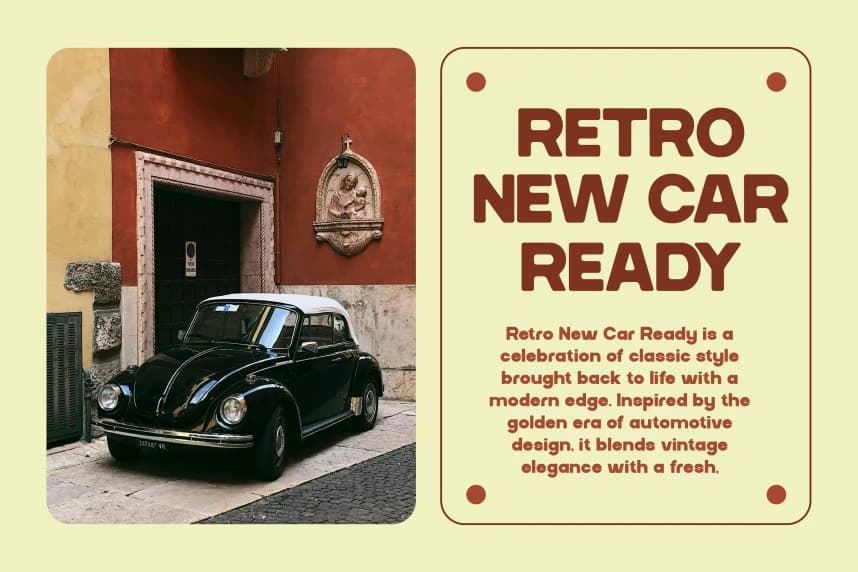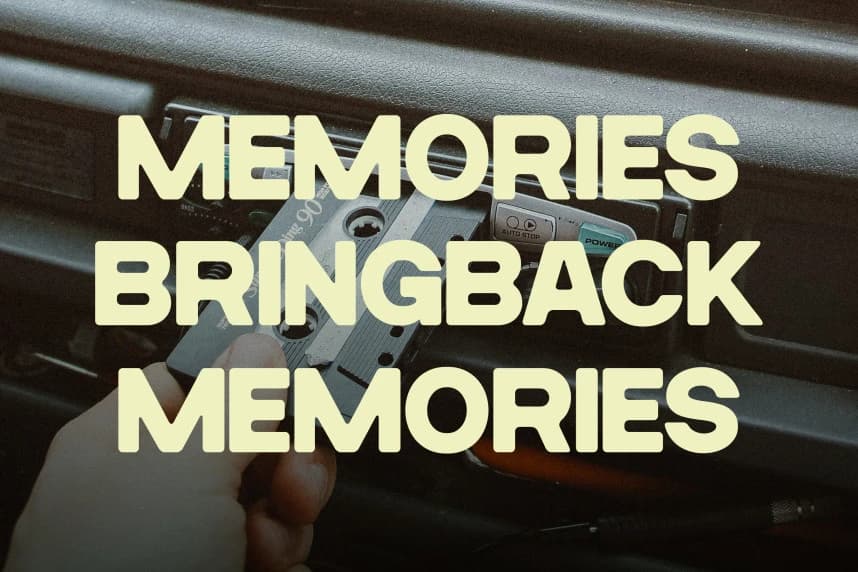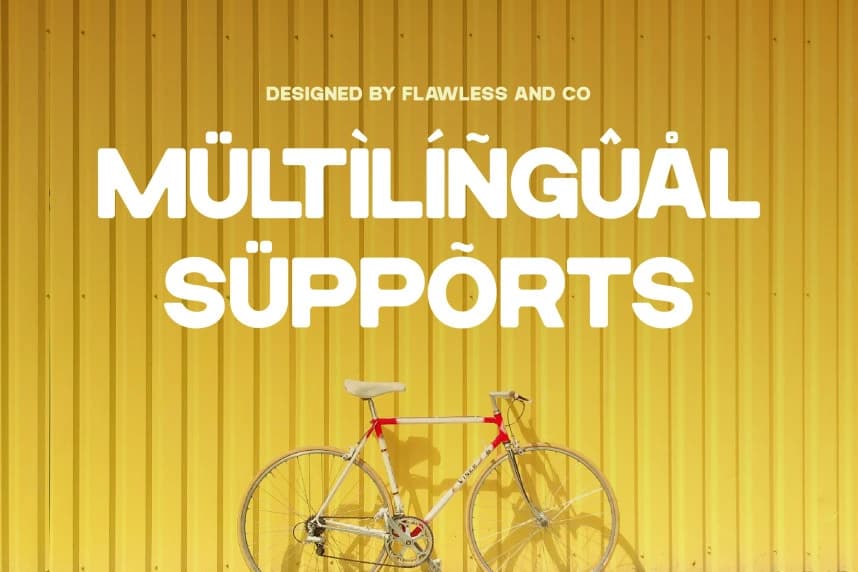
Maison Cronne Font
Maison Cronne Font, güçlü vintage esintiler ve cesur kişilikle harmanlanmış modern bir retro sans-serif yazı tipidir. Klasik tipografi stillerinden ilham alan bu font, yuvarlak hatlara ve nostaljik detaylara sahip olup sıcak ve ifade dolu bir görsel his yaratır.
Maison Cronne Font, güçlü vintage esintileri ve cesur bir kişiliğe sahip olan modern bir retro sans serif yazı tipidir. Klasik tipografi stillerinden ilham alan bu yazı tipi, yuvarlak hatlar ve nostaljik detaylara sahip olup sıcak ve ifadeli bir görsel hissiyat yaratır.